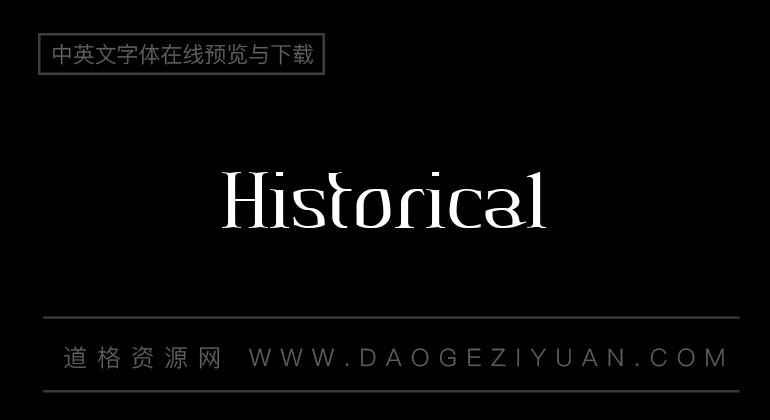
Historical 字体是一种仿古字体,用于模拟历史时期的手写字体。这种字体风格通常比较古朴、传统,带有一种古老的艺术气息。Historical 字体是很多设计师在设计书籍、海报、印刷品等历史相关作品时常用的字体之一。 这种字体有很多变体和风格,比如黑体、衬线体、手写风格等。Historical 字体的种类也很多,比如Trajan、Garamond、Baskerville、Palatino等等。这些字体都有自己的特点和应用场景。 Historical 字体在设计中的应用非常广泛,常见于书籍、历史文献、印刷品、标志设计等等。这种字体通过模拟古代手写字体的风格,营造出一种历史感和文化氛围,让人感受到历史的厚重感和深刻性。内容介绍
Historical是一款非常不错的手写艺术字体,具有很好的视觉感,适合于文化类的宣传设计、商业类品牌的广告和产品包装设计以及个性化文字排版等较多场景。